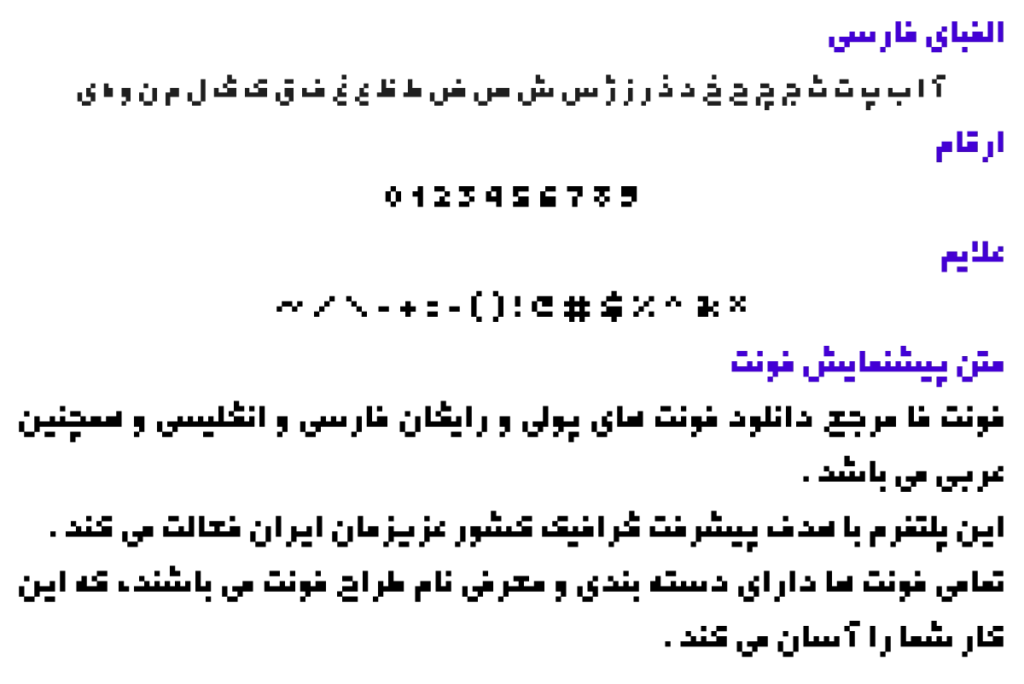
فونت فارسی سورنا – Sorena
طراح فونت: محمد درویشی نوع فونت: فونت پیکسلی
توضیحات و معرفی فونت سورنا
فونت فارسی سورنا ( Sorena ) از مجموعه فونت های آزاد می باشد، همینطور نوع فونت پیکسلی می باشد.
فونت زیبای مرتبط توسط محمد درویشی در سال 1403 طراحی و ساخته شده است.
سورنا در کوچک ترین اندازۀ پیکسلی طراحی و ساخته شده است.
از چالش های طراحی سورنا، حذف جزئیات در کنار وجود خوانایی بود.